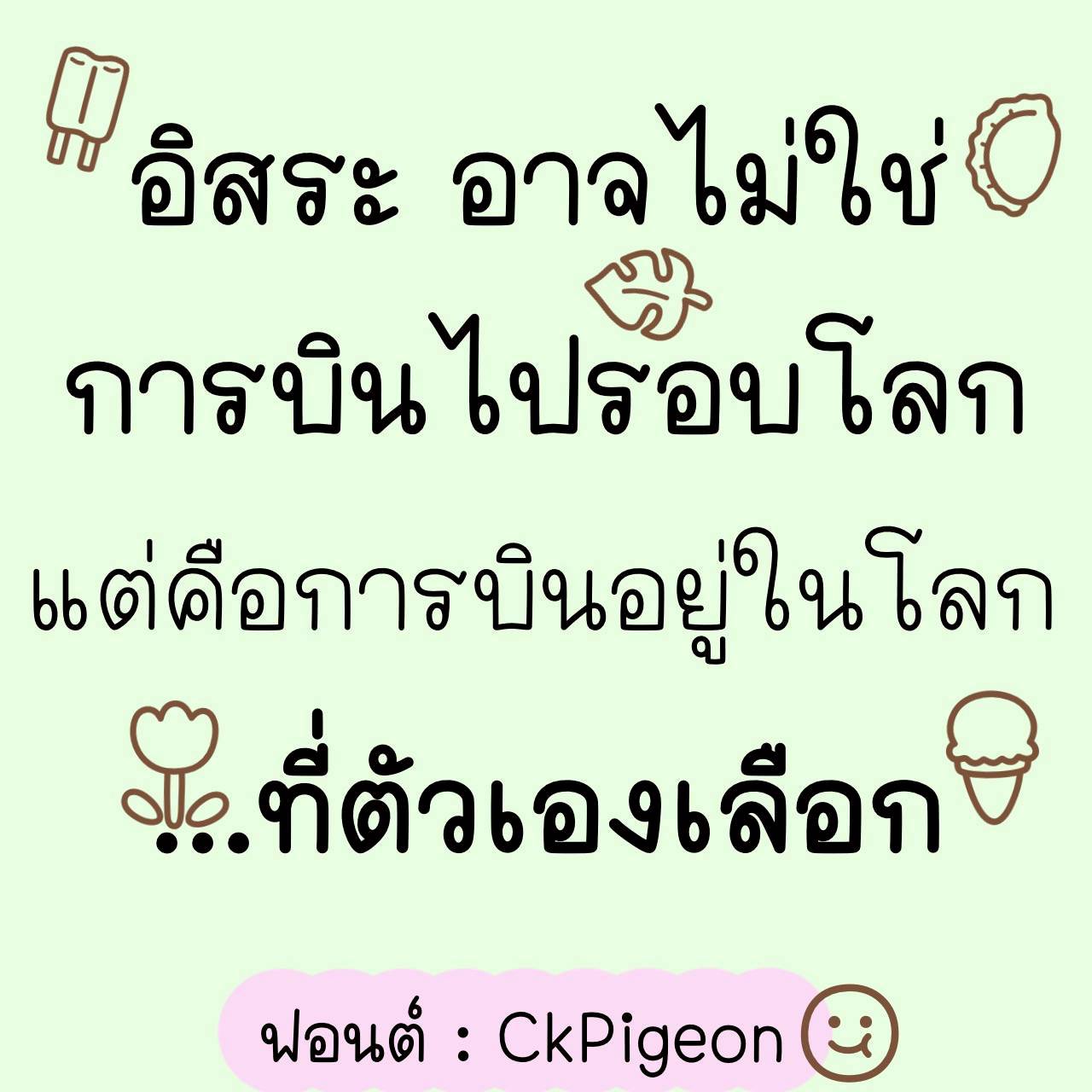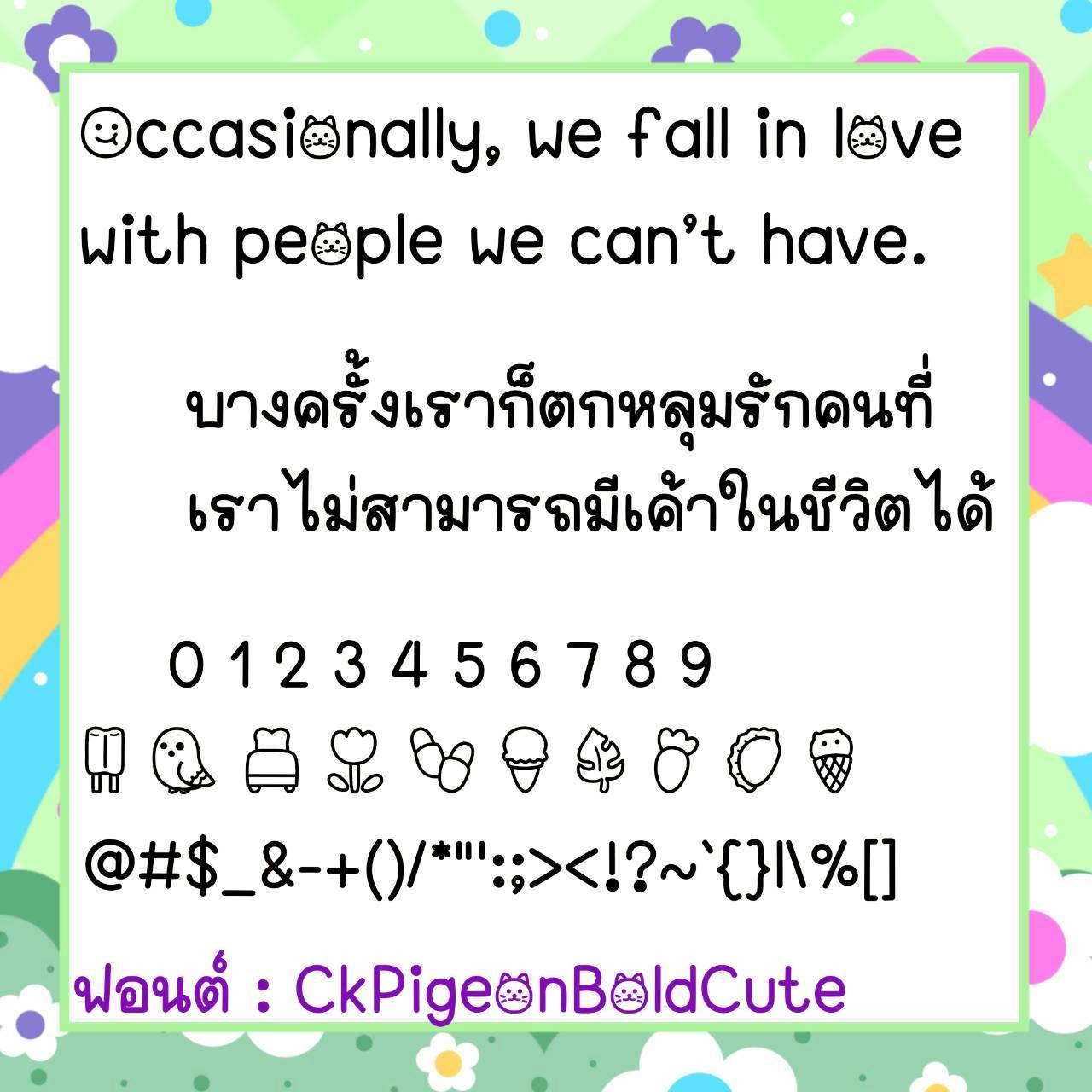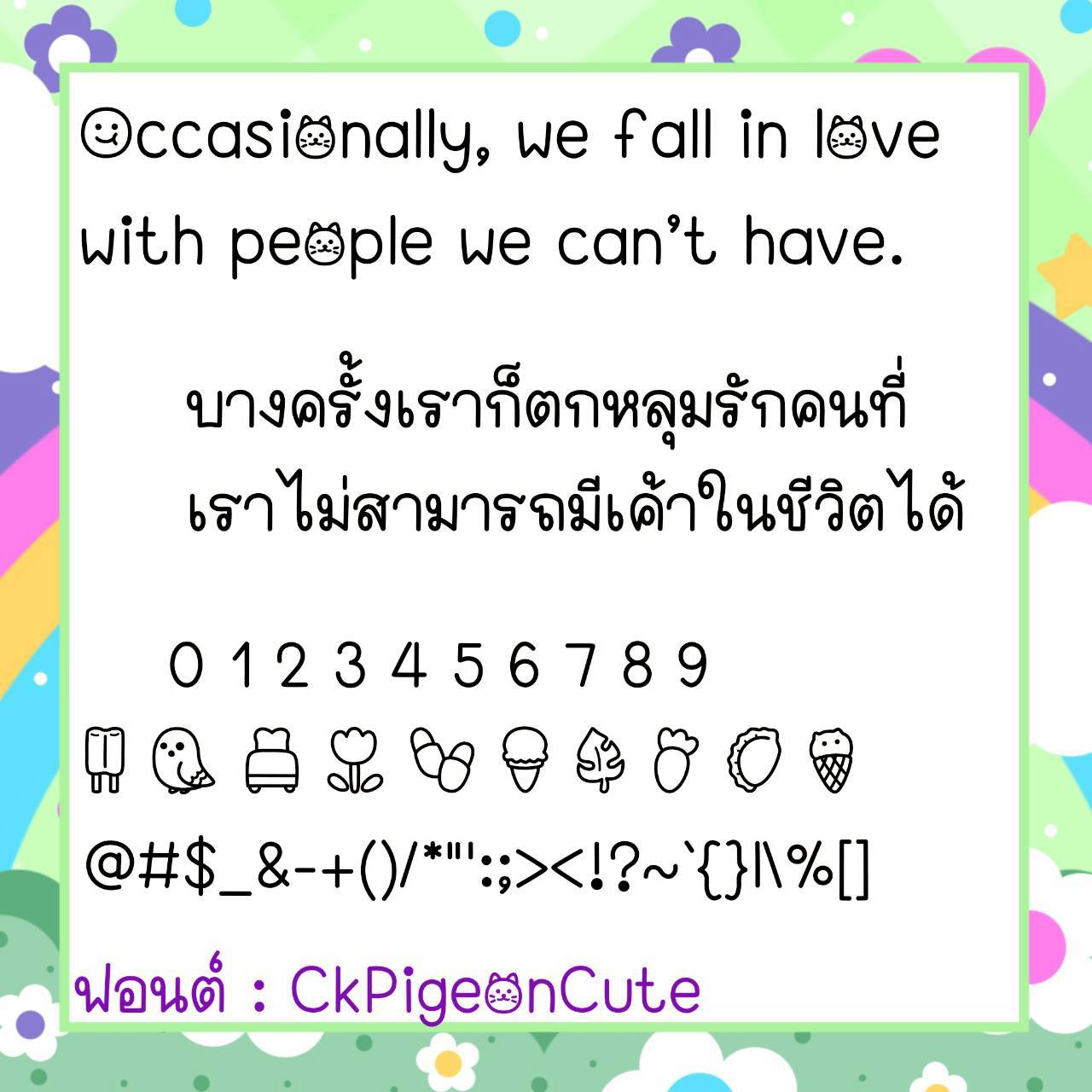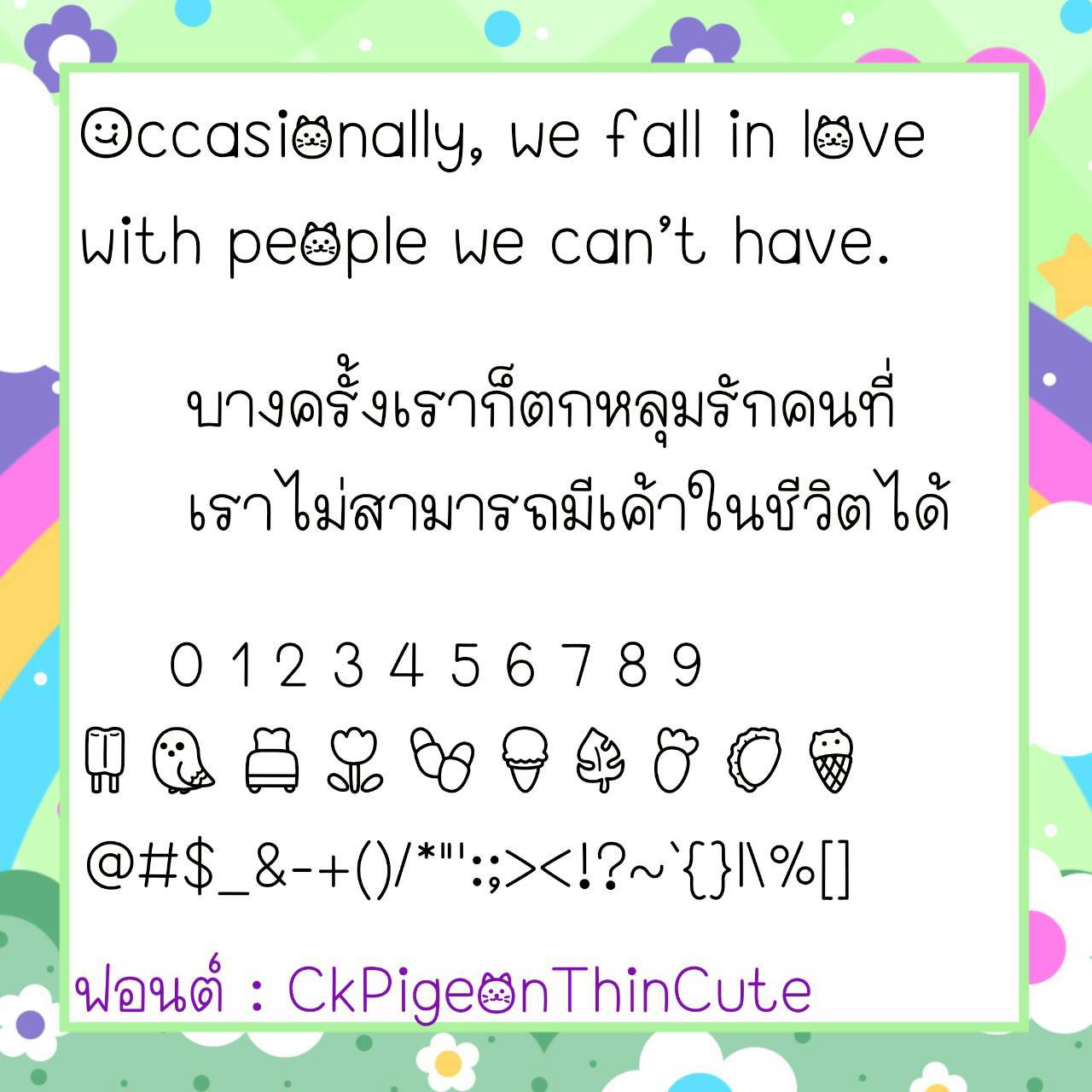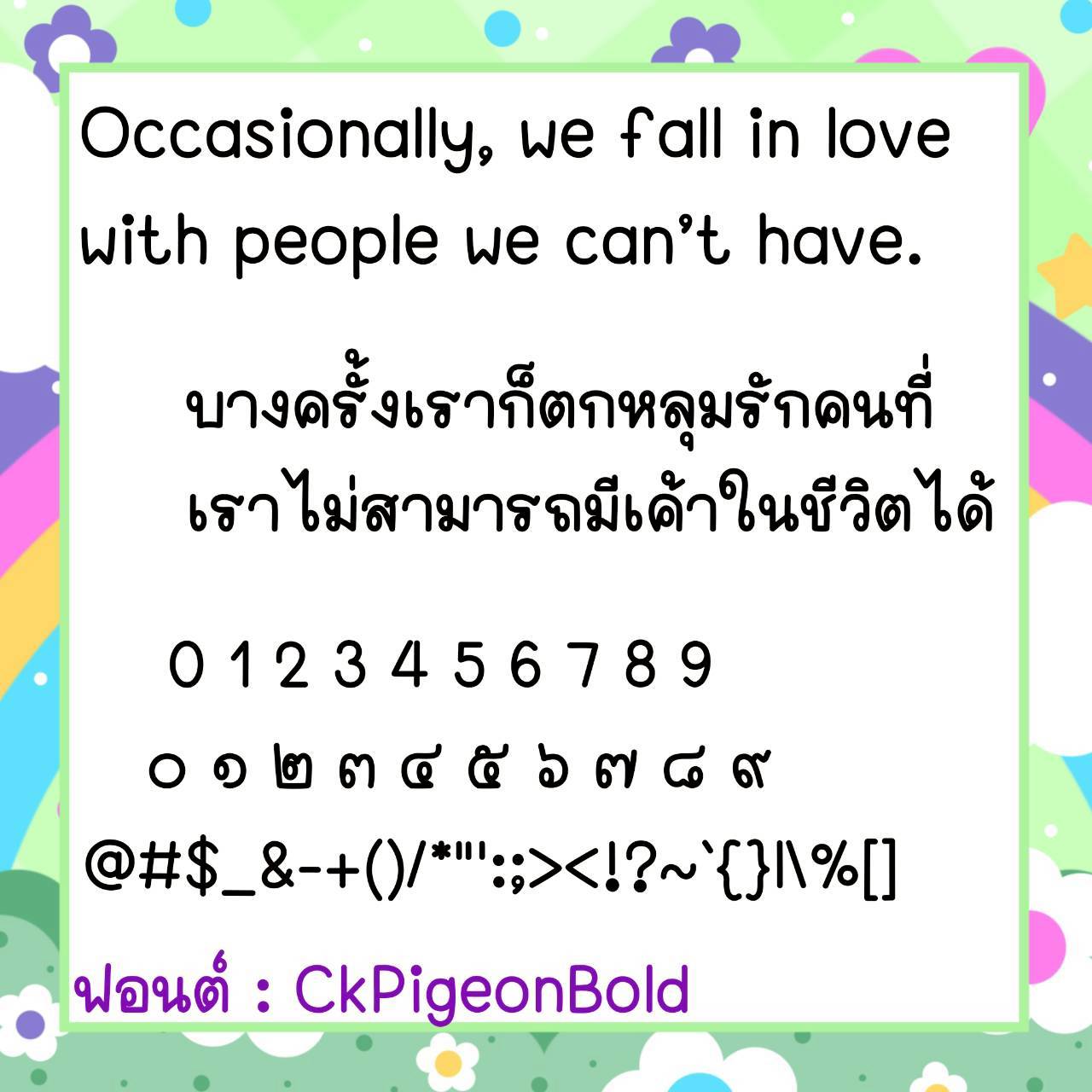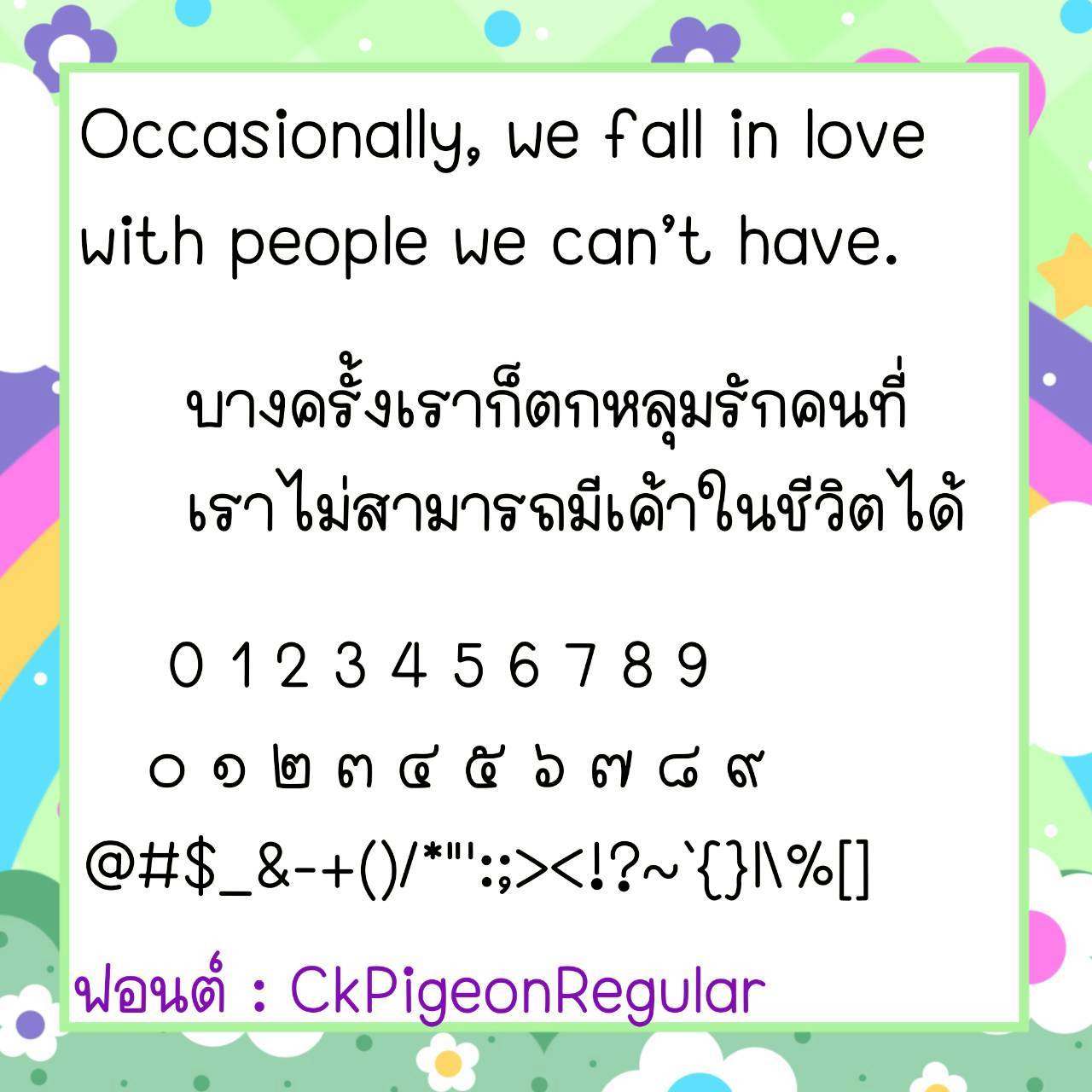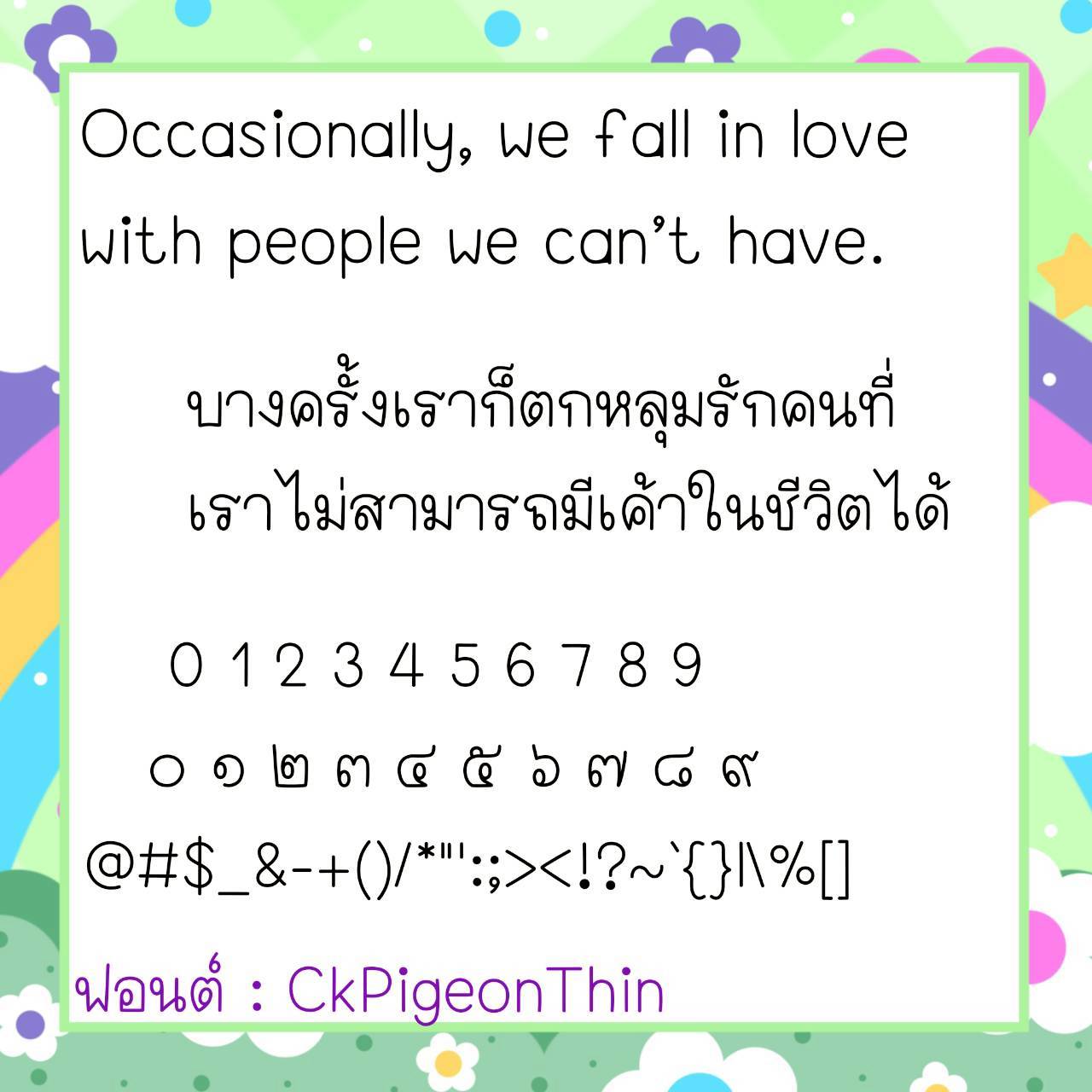
Font CkPigeon
🔸 ฟอนต์ลายมือแนวหัวมนๆรีๆ ตัวฟอนต์กึ่งเหลี่ยมในตัว ดูมีความกึ่งเป็นระเบียบ อ่านง่ายสบายตา และยังมีไฟล์อิโมจิน่ารักๆ ที่ใช้แทนเลขไทยให้ด้วยค่ะ 🥰💙
🔹 Handwritten font with rounded, oval heads, semi-square fonts, looks semi-organized, easy to read, and comfortable to the eyes. There are also cute emoji files that can be used instead of Thai numerals. 🥰💙